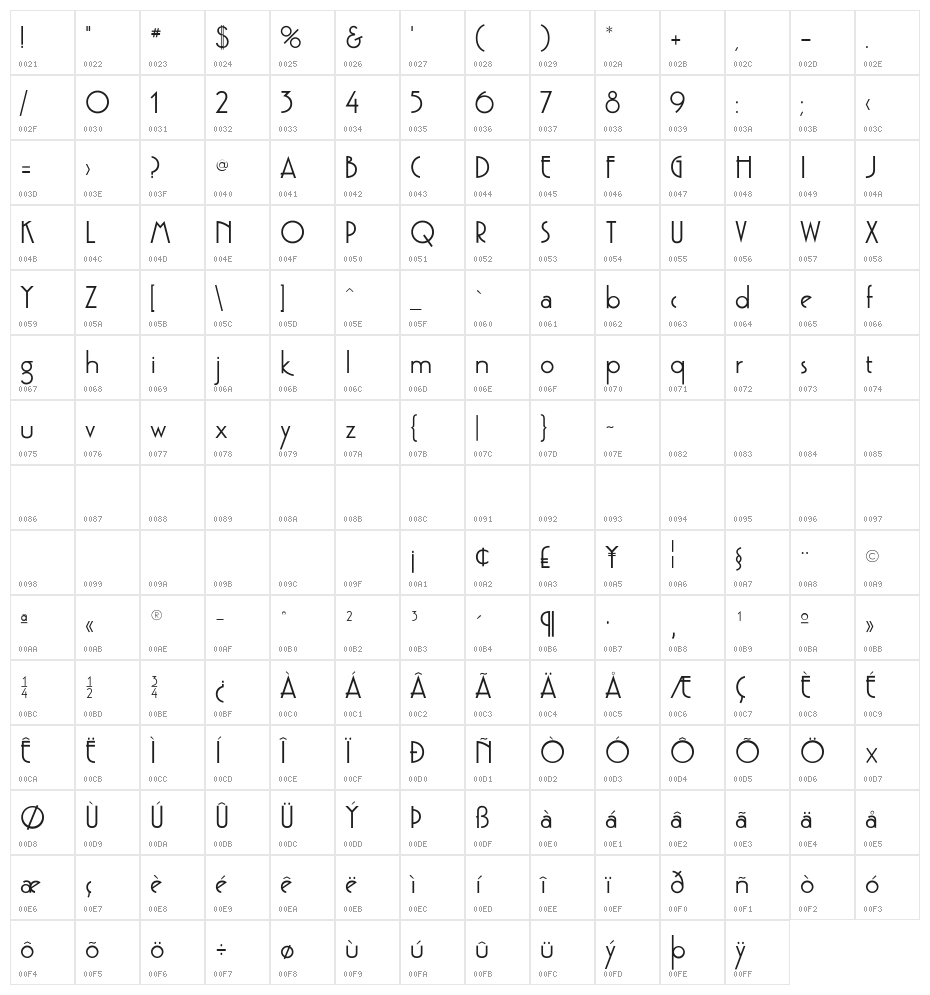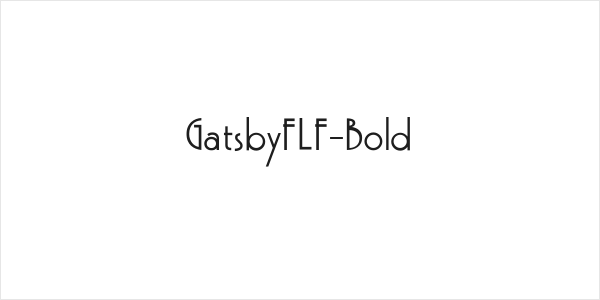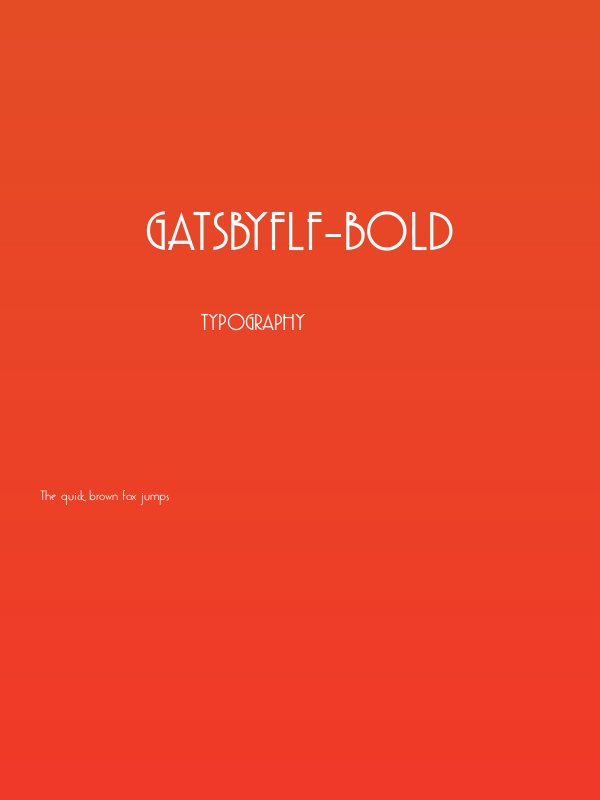
GatsbyFLF-Bold Font
✎ Art Deco
| Gesamtstil | Vintage |
| Vorgeschlagene Projekte | Ideal for branding, posters, and editorial design where a vintage yet modern look is desired. |